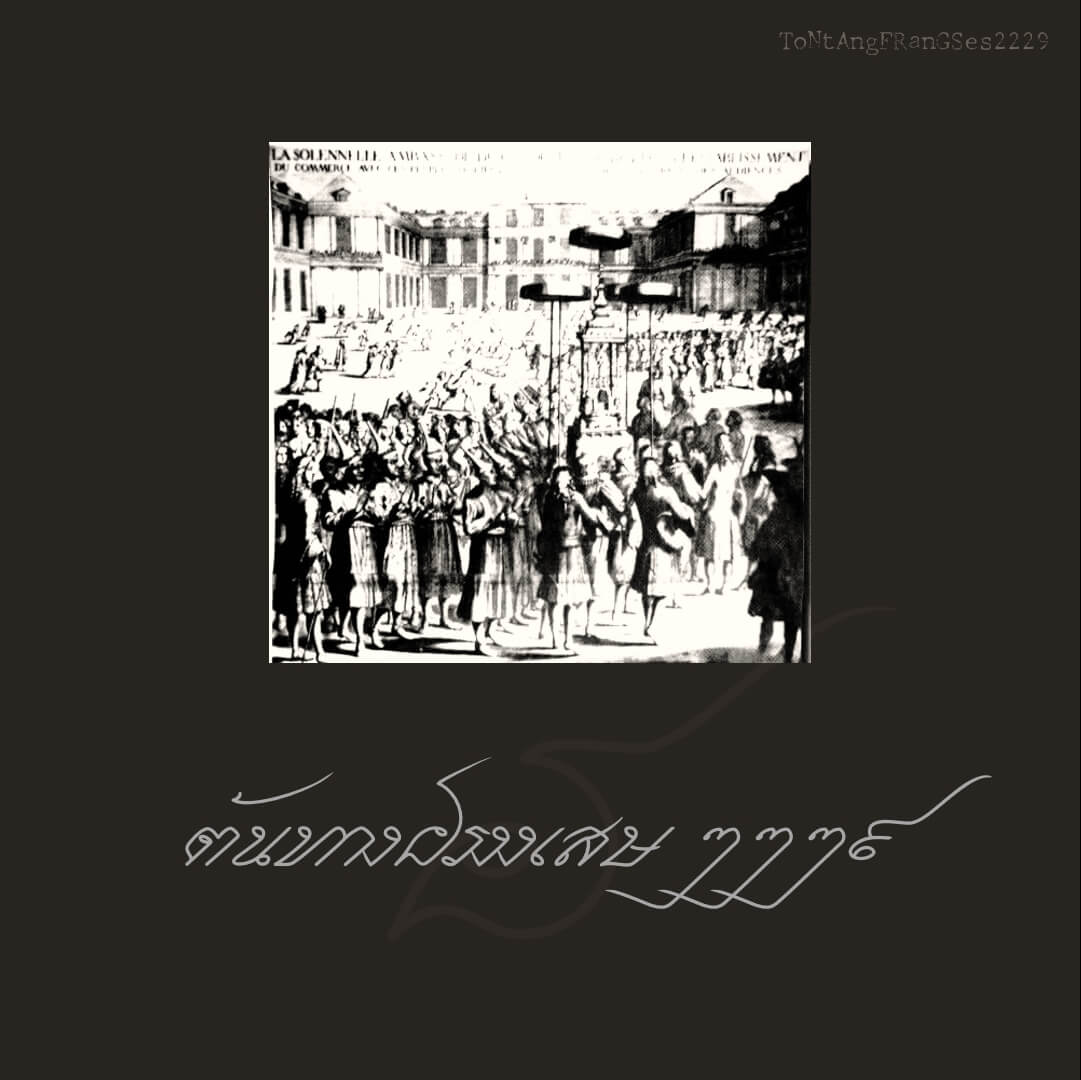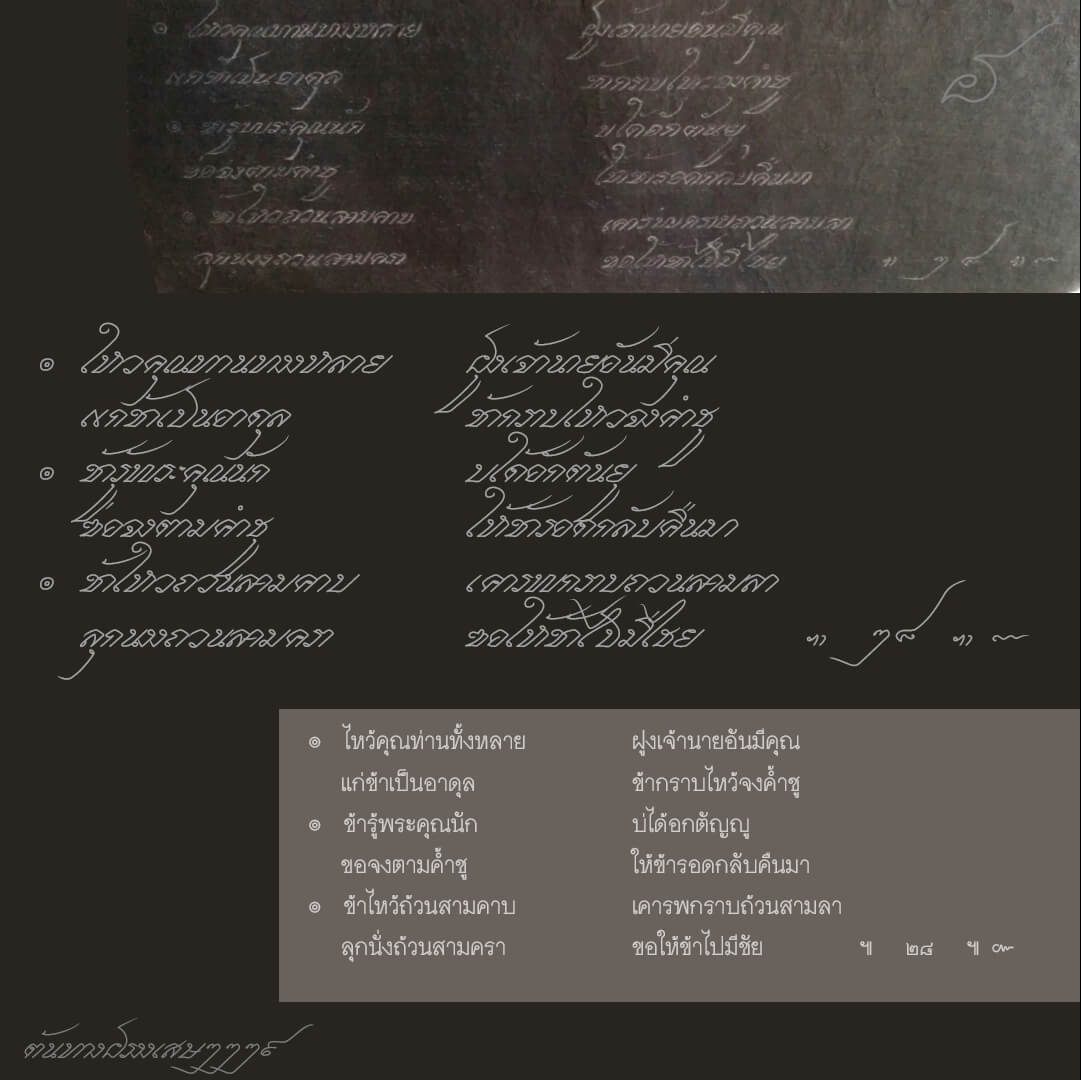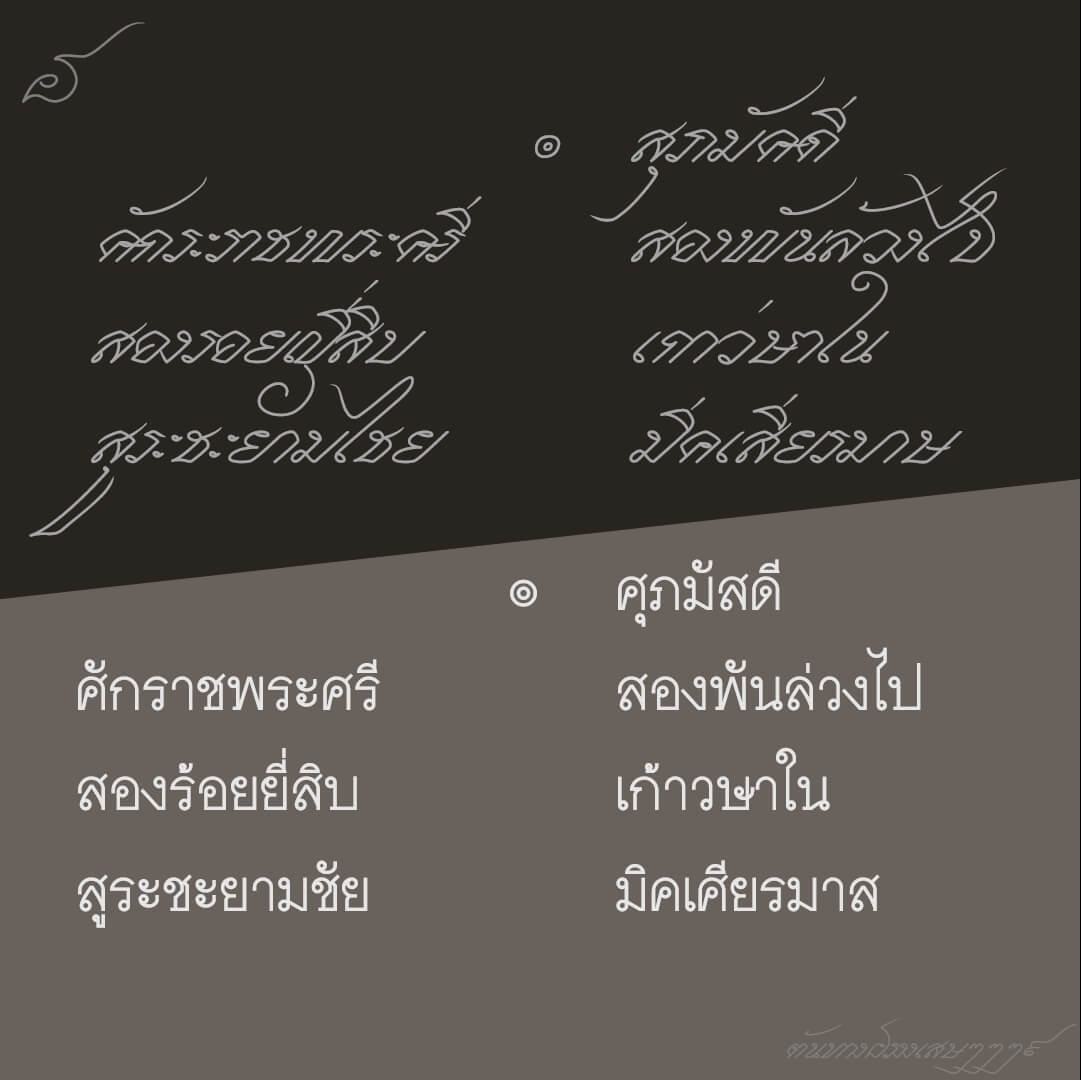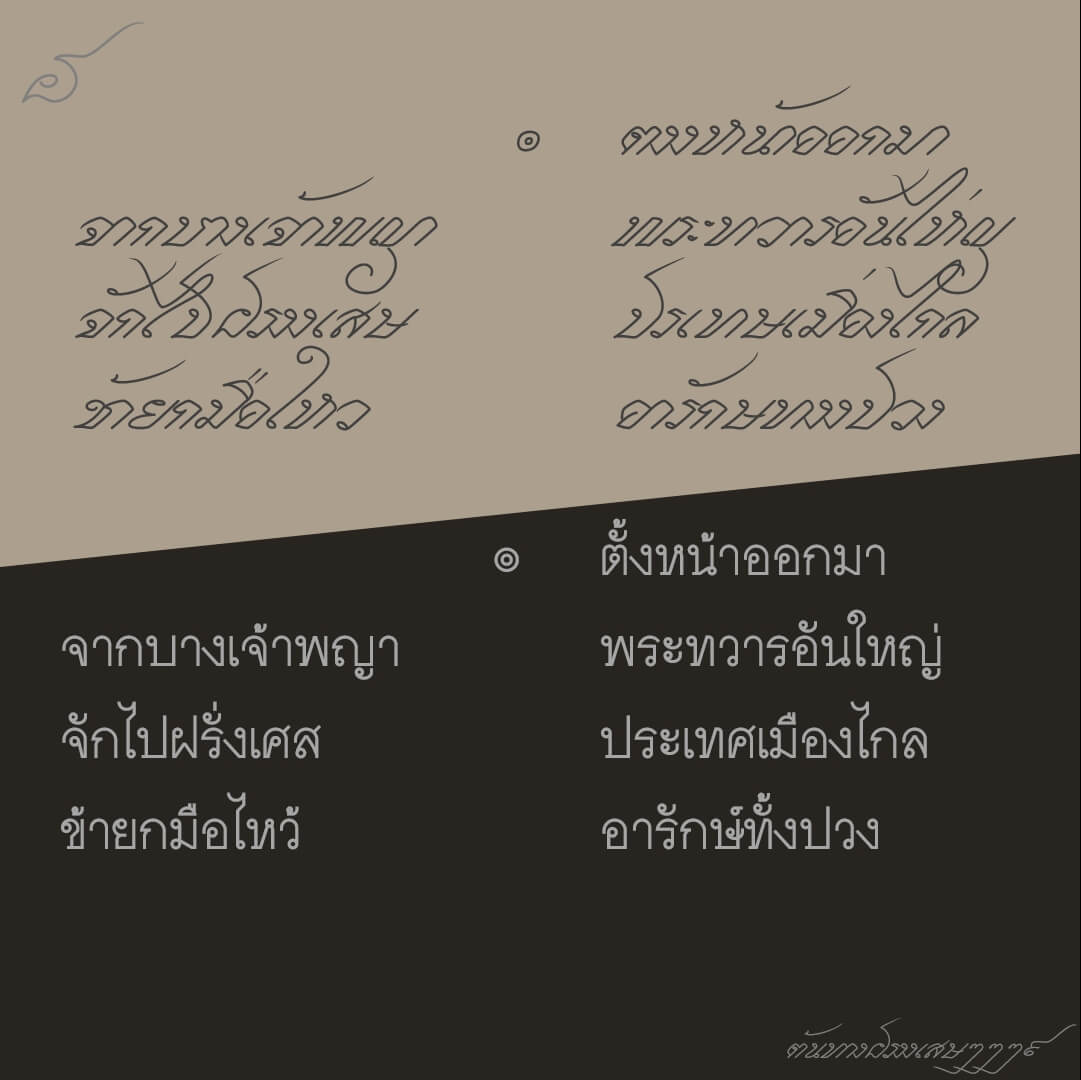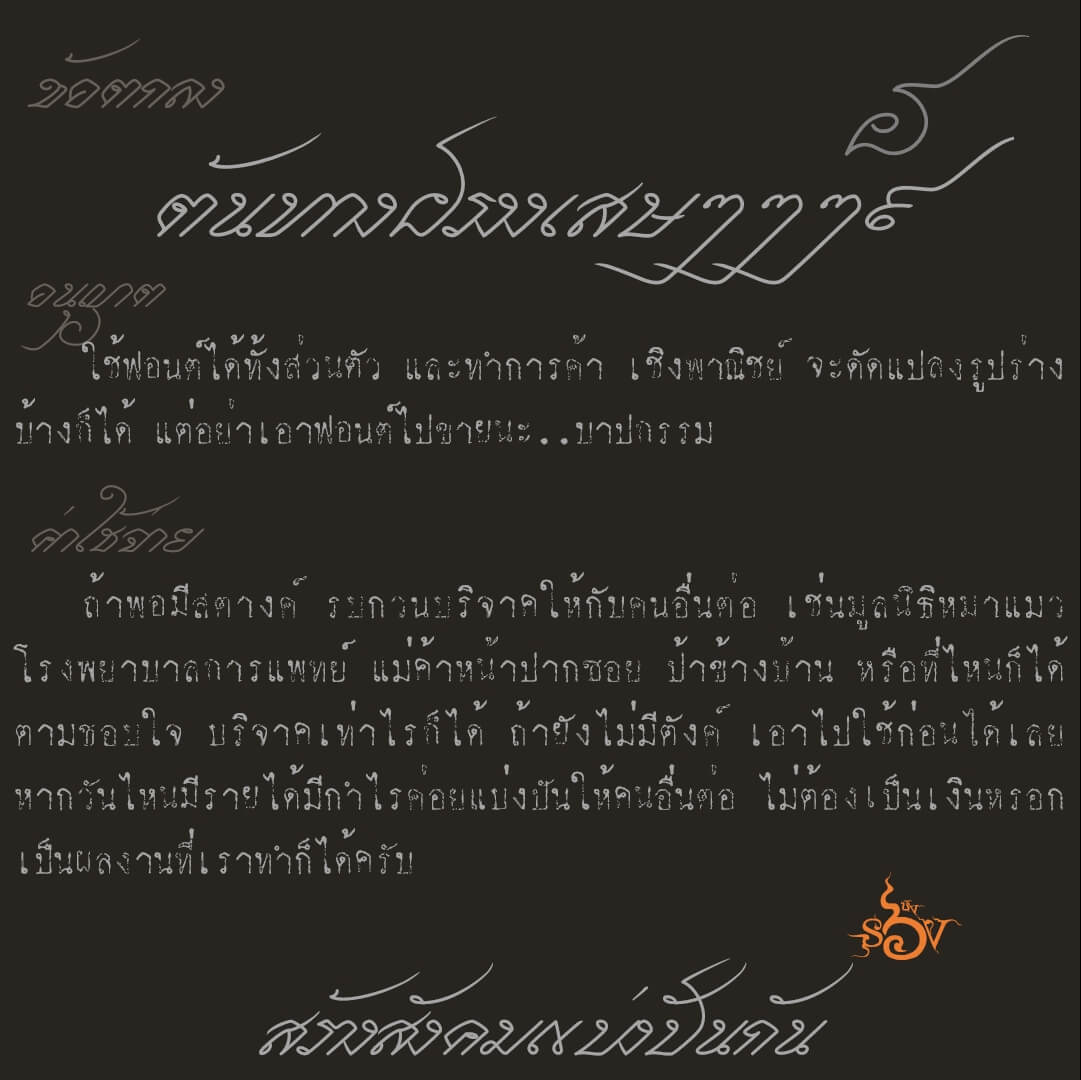
ต้นทางฝรงงเสษ๒๒๒๙ (SOV_ToNtAngFRanGSes 2229)
ฟอนต์ ต้นทางฝรงงเสษ๒๒๒๙ (ฝรงง อ่านว่า ฝรั่ง, ฝรงงเสษ อ่านว่า ฝรั่งเศส) ถอดแบบจากตัวอักษรไทยย่อ สมัยอยุธยา พ.ศ.๒๒๒๙ ในเอกสารชื่อ “ต้นทางฝรงงเสษ” บันทึกเรื่องราวเมื่อคราวที่คณะทูตไทยเดินทางทางเรือไปฝรั่งเศสในสมัยสมเด็จพระนารายณ์มหาราช
หมายเหตุ : แบบอักษรไทยในฟอนต์ตัวนี้มีไม่ครบทุกตัวอักษร เนื่องจากไม่พบในบันทึกนี้ (หรือผ่านตาไป หากผู้รู้ท่านใดพบเห็นอักษรที่หายไป รบกวนแจ้งให้ทราบเพื่อแก้ไข)
หมายเหตุ 2 : ตัวอักษรหลายตัว แม้พบในเอกสารฉบับอื่นในช่วงเวลาเดียวกัน เช่น บันทึกรายวันและจดหมายของโกษาปาน แต่ไม่ได้นำมาเพิ่มเติม เนื่องจากรูปแบบอักษรที่ประดิษฐ์ขึ้นต่างกัน เว้นไว้แต่ตัวเลขไทย ที่มีการเพิ่มเติมเข้าไปโดยอ้างอิงจากบันทึกรายวันและจดหมายของโกษาปาน